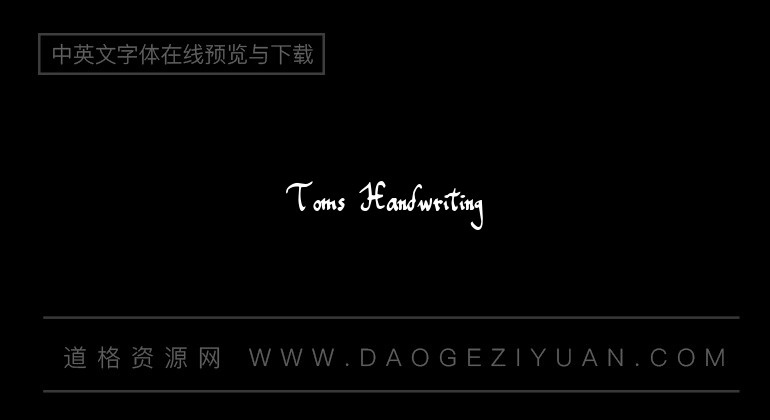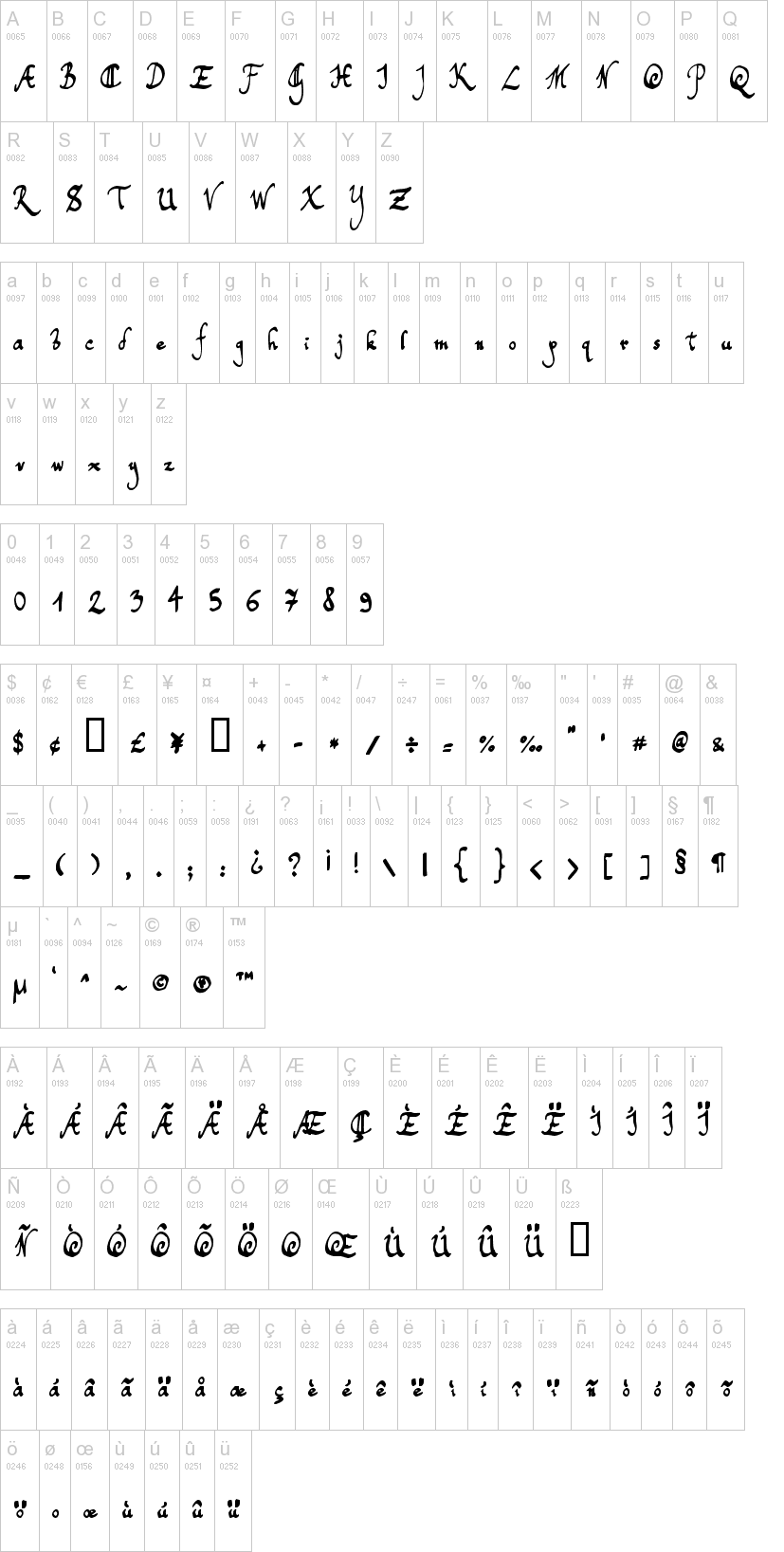
Toms Handwriting
Toms Handwriting 是一种手写风格的字体,设计师是 Tom Chalky。这种字体有很自然的流畅感,仿佛你正在读着作者的亲笔手迹一样。Toms Handwriting 有两种风格:一种是常规风格,另一种是粗体风格。这两种风格都非常适合用于个人或商业项目,例如名片、海报、标志、包装等等。由于这种字体的风格非常独特,因此它可以很好地引起人们的注意并增强品牌形象。
Toms Handwriting是一款非常不错的手写艺术字体,具有很好的视觉感,适合于文化类的宣传设计、商业类品牌的广告和产品包装设计以及个性化文字排版等较多场景。
Toms Handwriting字符映射图